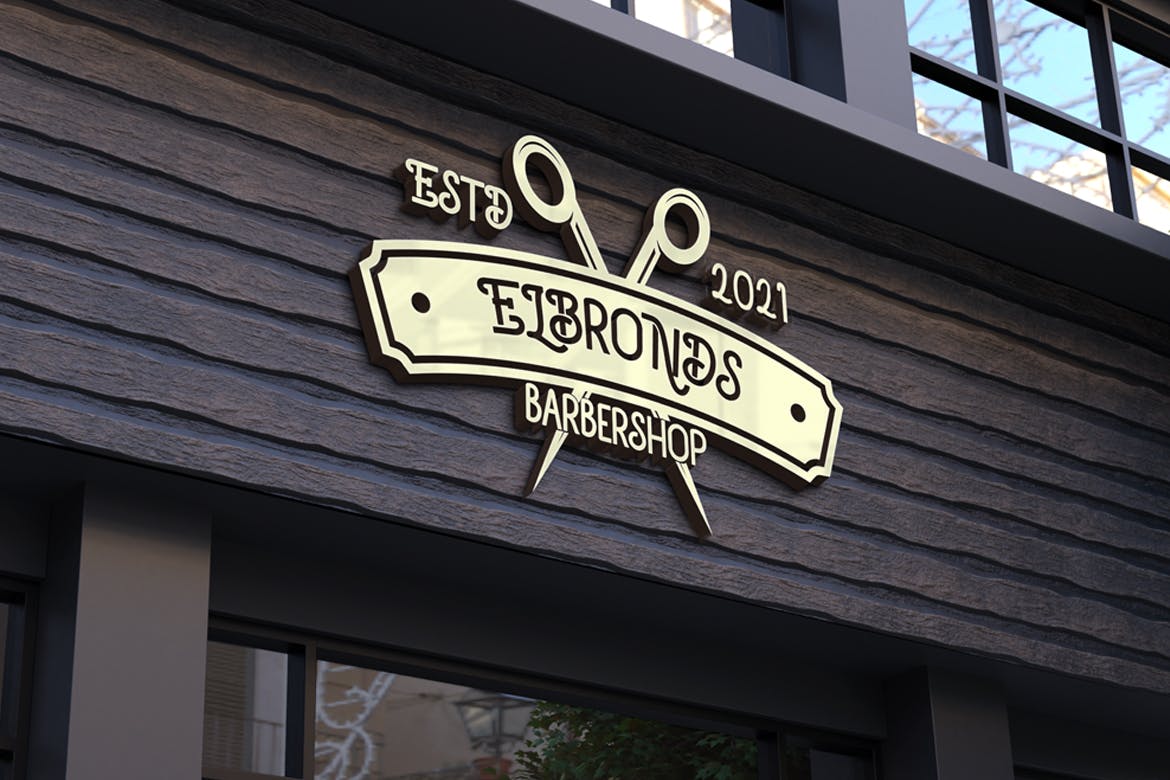
فونت گالگونا ترکیبی از حس زیبایی، سادگی و طراحی وینتج است که به عنوان یک فونت اسکریپت، توجه هر بینندهای را به خود جلب میکند. این فونت با استفاده بینقص از استایل سریف، جذابیت خاصی دارد و میتواند به طور گستردهای توسط افراد در پروژههای روزمره مورد استفاده قرار گیرد. چه در حال طراحی کارت ویزیت، بستهبندی، لوگو یا حتی یک مجله باشید، فونت گالگونا فرصتهای جدیدی را برای هر نوع استفادهای فراهم میکند.